Se acercan las Navidades y, a no ser que seas un poco Grinch (ya dedicamos un lettering navideño para estas personas en este artículo), la verdad es que apetece más que nunca sacar los pinceles para hacer postales navideñas DIY con lo que sabemos de lettering y de caligrafía. Este año he querido hacer una propuesta distinta, y en vez de hacer la postal con lettering, me ha apetecido utilizar las florituras de caligrafía para hacer el dibujo de un árbol de Navidad con florituras, así, se mezclan ambas disciplinas con un resultado bastante curioso. ¡Vamos a ver los materiales necesarios y el paso a paso!
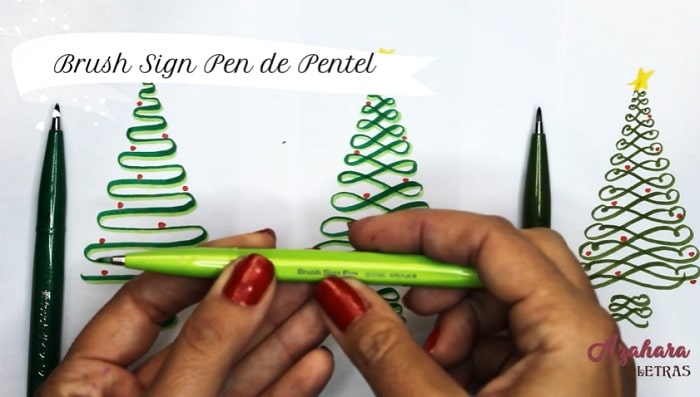
Tutorial paso a paso
Paso 1: Dibujar triángulos con lápiz
El primer paso es muy sencillo, tan solo se tiene que dibujar un triángulo isósceles y adecuarlo al tamaño de la punta del pincel. Es decir, si la punta del pincel es pequeña, bastará con un triángulo con una base de 5 cm, mientras que si la punta del pincel es de tamaño medio, el triángulo tendrá que ser más grande, de unos 7-8 cm, y si es un rotulador de punta de pincel grande, entonces la base tendrá que ser de unos 10 cm.
Como yo utilizo un rotulador de punta de pincel pequeña, el triángulo isósceles tiene una base de 5 cm.
Paso 2: Dibujar las Florituras
Hay muchos tipos de florituras que se pueden aplicar para dibujar los árboles de Navidad, en este caso he elegido tres muy sencillas. El proceso es igual en las tres: primero se realiza la floritura siguiendo el triángulo dibujado, después se repasan con un color más claro por debajo, como si fuese una sombra, y finalmente y de manera opcional, se dibujan las bolitas del árbol de Navidad y la estrella. Veamos cómo quedan estas tres florituras cuando se sigue este proceso:
Floritura ondulaciones
La primera floritura es muy sencilla, ya que solo se tienen que hacer ondulaciones o «eses», cada vez más anchas y ajustándose al triángulo que hemos dibujado, combinando trazos finos con trazos gruesos, tal y como se ve en la imagen. Si esto no lo entiendes, es mejor que mires el vídeo. Después, se repite el proceso pero con un color más claro, somo si fuese la sombra por debajo.
Floritura lazo
La segunda floritura es algo más compleja, pero no es muy difícil, solo hay que ir dibujando una especie de lazo, también con trazo fino cuando vas de izquierda a derecha y trazo grueso cuando vas de derecha a izquierda. De nuevo, si esto no lo entiendes o no lo dominas, echa un ojo al vídeo. Después, se repite el esto mismo pero con un color más claro, para hacerle un efecto de profundidad o de sombra por debajo.
Floritura «corazón»
La tercera floritura es algo más difícil, ya que combina el lazo con una especie de bucle pequeño que hace que la floritura tenga cierto aspecto de corazón alargado, por así decirlo. La dinámica es la misma de trazo fino hacia un lado y grueso hacia el otro. En este caso, no se realiza sombra, ya que la floritura es suficiente per sé.
Como en las anteriores, se puede dibujar las bolitas y la estrella de manera opcional.